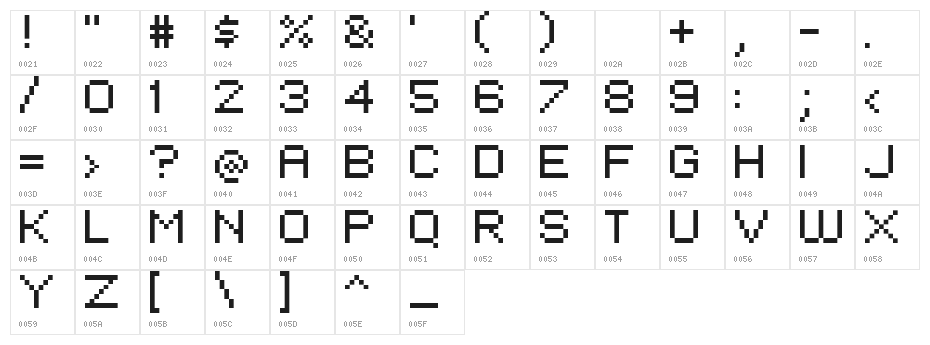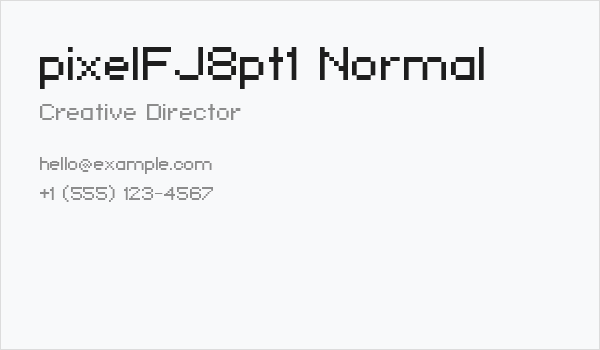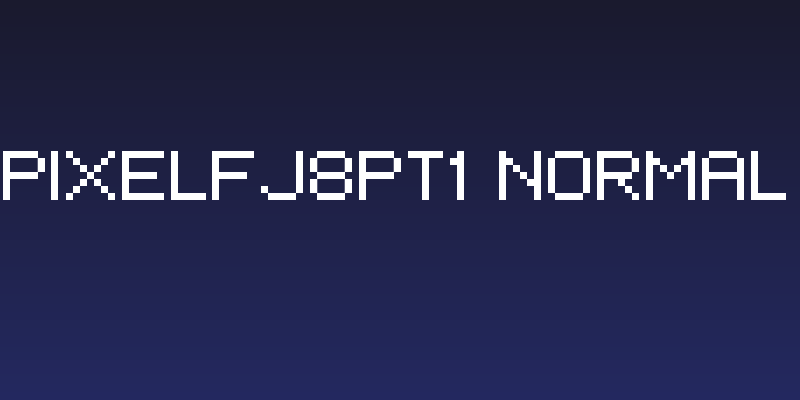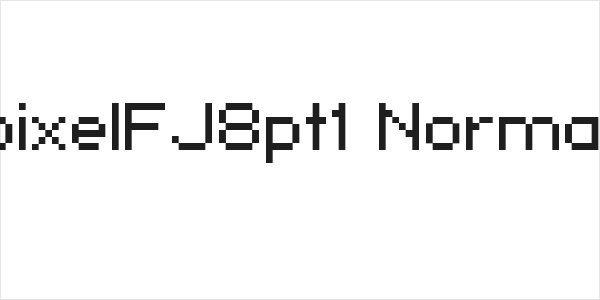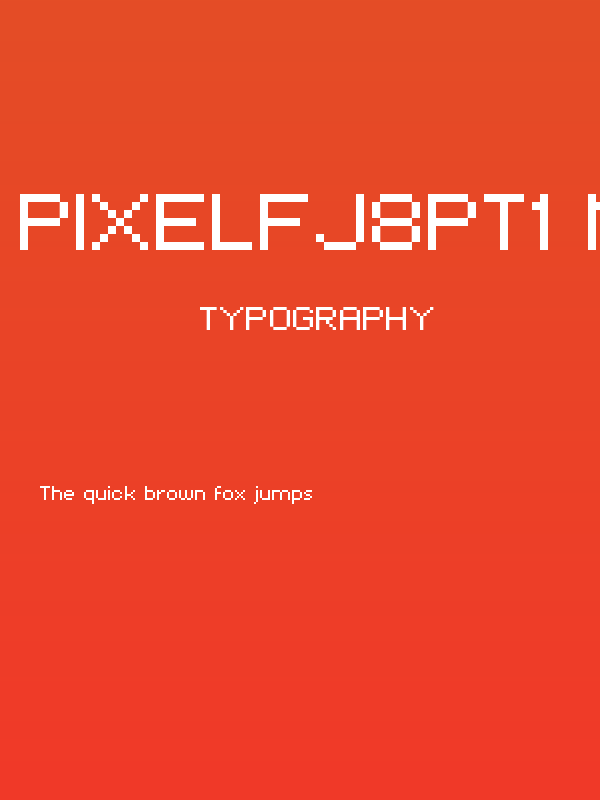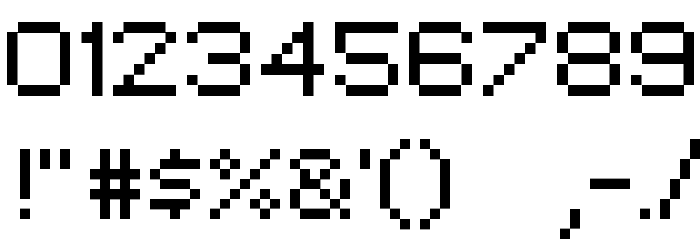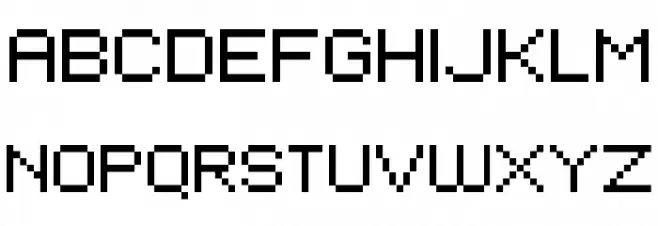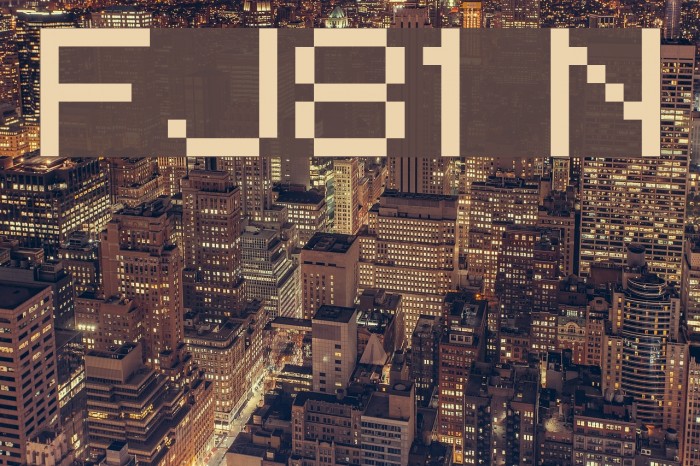
pixelFJ8pt1 Normal Font
✎ Pixel
| Kategorien | Pixel |
| Gesamtstil | Retro |
| Anwendungsfall | Digital displays, video game text, retro-themed designs. |
| Vorgeschlagene Projekte | Ideal for retro video games, digital art projects, and any design work that requires a nostalgic or minimalist digital look. |